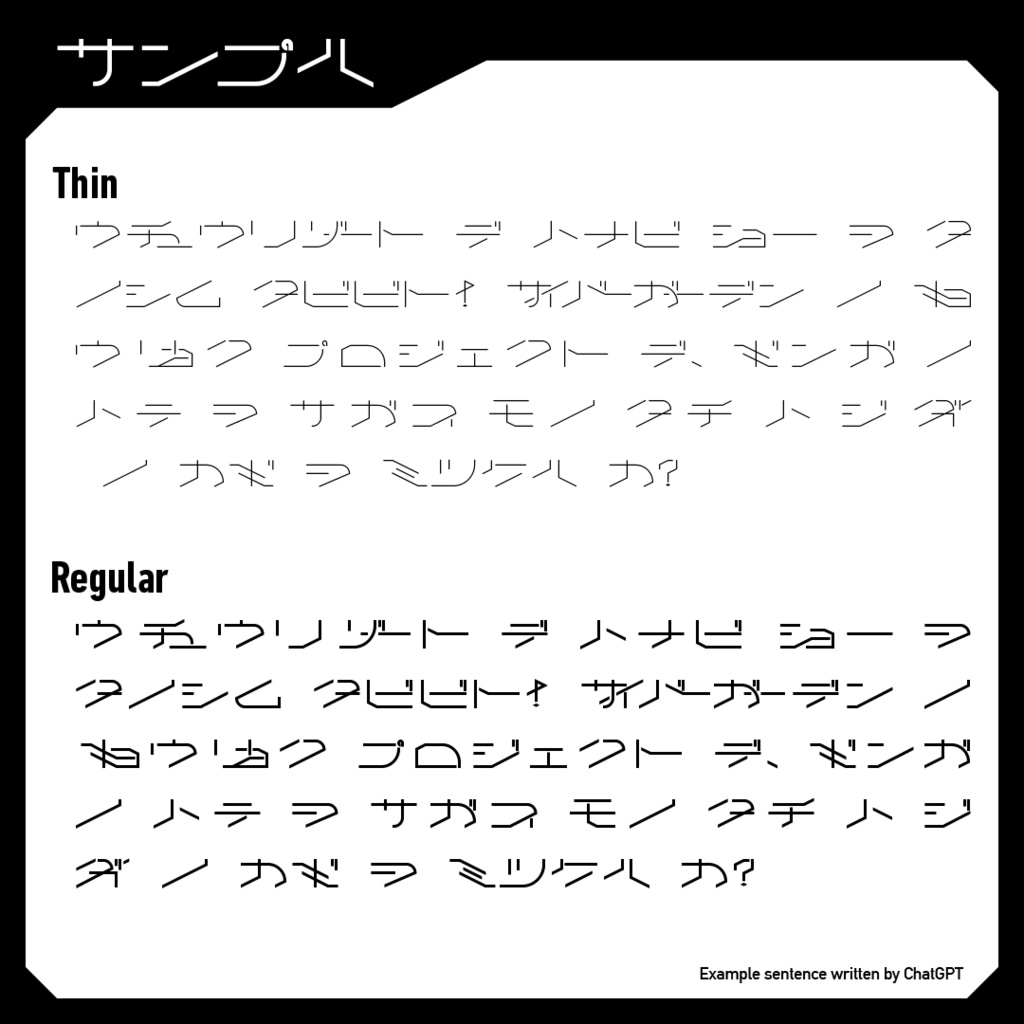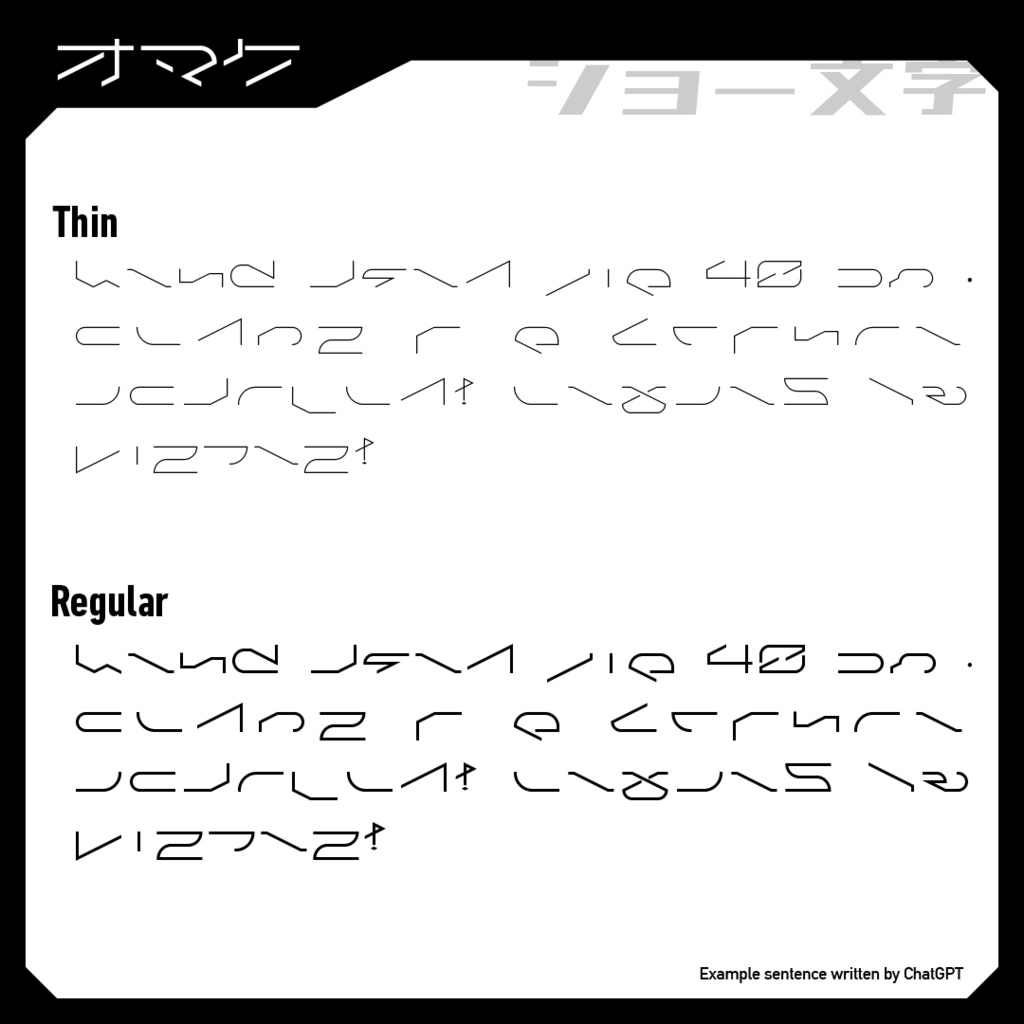
アングルコード【フリーフォント版有り】
リガチャが特徴的なカナフォントです。 カナ文字入力すると勝手につながって、大体そのままロゴっぽくなります! カナフォントとして制作しましたが、おまけに〼、〽、蘇州号碼(及び付随する一部漢数字)、ショー文字という明らかに要らない文字を収録しました。 【フォント仕様】 カタカナ(リガチャ有り)・数字・一部記号・蘇州号碼・一部漢数字・ショー文字 417グリフ収録 OpenTypeフォント 【フォント仕様(フリー版)】 カタカナ(リガチャ制限)・数字・一部記号・ショー文字 284グリフ収録 OpenTypeフォント ●利用について - 個人・商用利用可 - ロゴデザイン制作の際にアウトライン化/画像化しての加工可 - 詳細は同封のテキストファイルをご参照ください